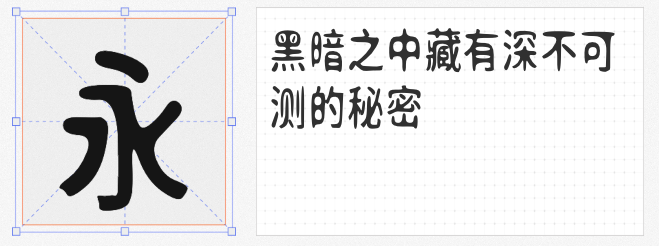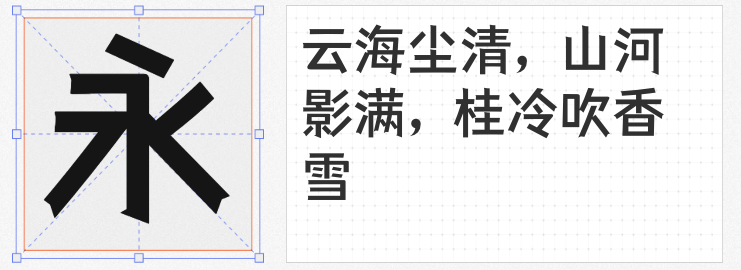
新春伊始,设计界迎来创作热潮,如何让开年海报在视觉上脱颖而出?选对字体是关键!本文精选四款风格鲜明、可免费商用的字体,助你轻松打造兼具个性与品牌调性的视觉作品。
1. 站酷小薇LOGO体
这款字体以“剑”为灵感,笔画修长如刃,兼具谦和与灵秀气质。设计团队大胆简化部分笔画,却通过独特的结构平衡保留了高识别度。无论是科技品牌海报的未来感,还是文化活动的东方韵味,它都能以利落的线条传递锐意进取的视觉语言,尤其适合需要突出品牌标识的场景。
2. 斗鱼追光体2.0
作为直播平台斗鱼的定制字体,斗鱼追光体2.0承载着企业“活力、上进、娱乐”的基因。设计师通过几何化笔触与动态倾斜角度,赋予文字跃动的节奏感,同时以模块化结构确保多场景适用性。无论是电竞活动海报的热血氛围,还是科技产品发布的极简风格,这款字体都能以统一视觉语言强化品牌记忆点。
3. 新愚公迷茫体
基于思源黑体的颠覆性改造,这款字体通过随机扭曲效果模拟“融化”的视觉意象,营造出迷幻而富有张力的氛围。其非常规的笔画形态适合作为海报的视觉焦点,尤其契合音乐节、艺术展等需要突破常规的设计场景,为作品注入先锋艺术气质。
4. 仓耳与墨 W03
取苏轼词中“窈窕”之境,这款字体以粗细渐变的笔形与圆润轮廓,勾勒出慵懒而优雅的东方韵味。相比传统书法字体,它更注重现代设计的平衡感,既适用于新春贺岁海报的喜庆氛围,也能为文创产品宣传增添雅致格调,是传递文化底蕴的绝佳选择。
从锐意创新到艺术解构,从科技活力到东方雅韵,这四款字体覆盖多元设计需求,且均支持免费商用。新春设计不妨大胆尝试,让文字成为传递品牌态度的第一视觉语言!